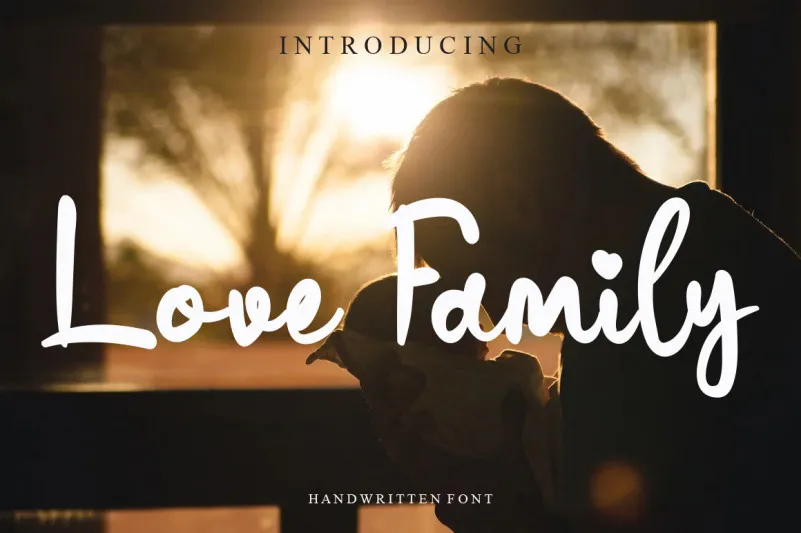
Love Family Font – Fonte Grátis
Love Family Font
Esta é uma fonte de script leve com um tema descontraído, projetada para oferecer um estilo agradável yeno importe do tópico, essa fonte pode se tornar um ativo excepcionalmente valioso para seu banco de fonts. Ela tem o poder de transformar qualquer criação em algo incrivelmente especial e encantador. Seja você criando uma identidade visual, desenhando sua arte favorita ou até mesmo produzindo seus textos mais pessoais, a Love Family Font será um complemento que elevará seu design para outro nível. Com uma paleta de formas elegantes e uma disposição livre, ela oferece flexibilidade para adaptar a fonte aos diferentes contextos. Este é o tipo de fonte versátil que qualquer designer apaixonado pelo amor da família deve ter em sua coleção de fonts favoritas. Se você está procurando por um novo charme ou apenas deseja dar uma pitada mais pessoal e delicada para suas obras, a Love Family Font é definitivamente algo que vale a pena incluir na sua biblioteca fonte.